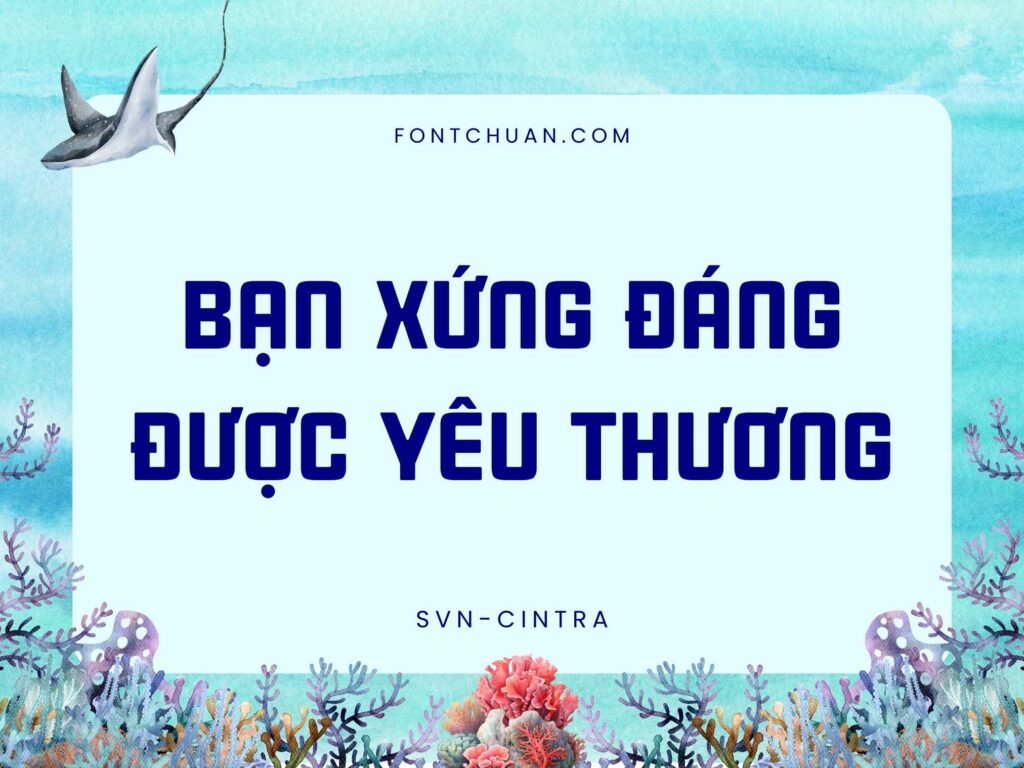
Font SVN Cintra Việt Hóa
Tác giả Font: Pablo Balcells
Cintra là một font chữ sans-serif đậm và hình học, được thiết kế bởi Pablo Balcells và phát hành bởi Graviton Font Foundry vào năm 2014. Font này nổi bật với các góc bo tròn nhẹ, mang lại vẻ mềm mại và dễ chịu cho người xem. Cintra đã được Việt hóa để hỗ trợ tiếng Việt bởi Styleno.1 Fonts, đồng thời hỗ trợ nhiều ngôn ngữ khác, giúp mở rộng phạm vi sử dụng trên toàn cầu. Font này được thành viên của Font Chuẩn sưu tầm và chia sẻ, đáp ứng nhu cầu của bạn đọc và ứng dụng thực tế vào các dự án thiết kế.
Đặc điểm thiết kế của Cintra bao gồm các đường nét đậm, hình học với góc bo tròn nhẹ, tạo cảm giác hiện đại và thân thiện. Font này phù hợp cho các ứng dụng như thiết kế tiêu đề, poster, logo và các dự án sáng tạo khác. Các ngành nghề phù hợp bao gồm quảng cáo, công nghệ và thiết kế đồ họa.